Typografischer Terminus für eine Randbemerkung außerhalb des Registers eines Satzspiegels bzw. außerhalb der Kolumnen eines Gestaltungsrasters. Etymologisch von »marginal« für »am Rand liegend« aus »marginalis« zu lt. »margo« für »Rand«. Marginalien zählen in der Buchgestaltung zu den Konsultationen.
Marginalien werden gerne als stichwortartige Hinweise und Begriffserläuterungen u.a. in Sach-, Fach-, Geschichts- und Lehrbüchern, Nachschlagwerken oder Geschäftsberichten verwendet. Marginalien sind eine Möglichkeit, dem Leser Zusatzinformationen zu einer bestimmten Textstelle in der Hauptkolumne anzubieten, ohne dadurch den Leseprozess zu stören. Marginalien können ebenso behilflich sein, komplexe Inhalte didaktisch zu strukturieren.
Randbemerkungen können ggf. auch Bildunterschriften oder Headlines ersetzten bzw. ergänzen. In einer Marginalkolumne können neben Text auch Bilder oder Illustrationen platziert werden, beispielsweise Diagramme bei Geschäftsberichten.
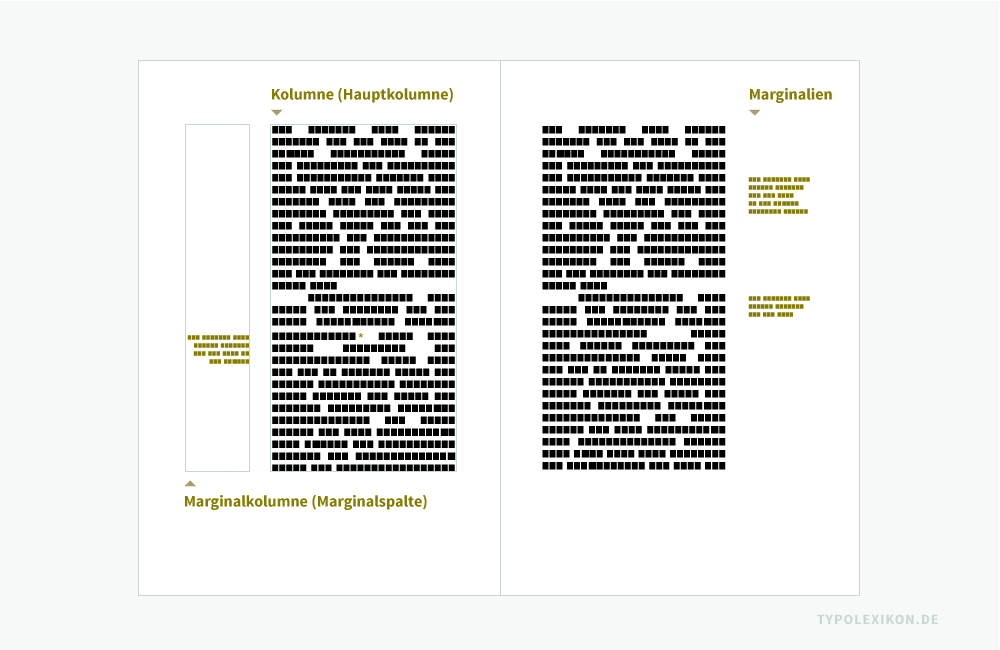
Marginalspalten
Marginalien werden bei Büchern oder buchähnlichen Publikationen in einer Marginalkolumne (Marginalspalte oder Marginalsatzspalte) außerhalb des Satzspiegels – in der Regel bei einer Verso-Seite im linken oder bei einer Recto-Seite im rechten Außensteg – eines Buchsatzspiegels 1) gesetzt. Bei großformatigen Büchern (z.B. Tischbüchern) können Marginalien auch im Bundsteg stehen. 2)
Registerhaltigkeit
Marginalien beginnen grundsätzlich immer auf der Schriftlinie der Zeile des Grundlinienrasters, auf welche sie Bezug nehmen. Die erste Marginalzeile ist folglich registerhaltig. Die zweite Zeile nebst Folgezeilen einer Marginalie kann dann vom Zeilenabstand (ZAB) der Hauptkolumne abweichen, beispielsweise in halben ZAB-Schritten (Halbzeilenraster). Unabhängig davon, sollten Marginalspalten auch bei einem ungewöhnlichen Zeilendurchschuss immer vertikal Register halten.
Konsultationszeichen
Falls keine Notenkolumne existiert oder kaum Fußnoten verwendet werden, können Marginalien zusätzlich mit Konsultationszeichen (Konsultation von lat. »consultatio« für »Beratschlagung«) verknüpft werden, beispielsweise mit Arabischen Ziffern.
Satzausrichtung
In der Buchtypografie sind Marginalien in ihrer Satzausrichtung zur Hauptkolumne hin angeordnet. Beim Blocksatz der Hauptkolumne ist die Satzausrichtung der Marginalien auf der linken Buchseite in der Regel rechtsbündig, auf der rechten Buchseite linksbündig. 3) Beim asymmetrischen Flattersatz der Hauptkolumne ist die Satzausrichtung der Marginalien auf der linken und rechten Buchseite in der Regel linksbündig.
Satzbreite
Marginalien werden in der deutschen Sprache in einer durchschnittlichen Satzbreite von mindestens zwei (z.B. bei langen Komposita) bzw. drei (bei durchschnittlichen Wortlängen) bis maximal sechs Worten (bei durchschnittlichen Wortlängen) gesetzt.
Schriftgrad
Marginalien werden in der Lesetypografie in einer Konsultationsgröße (Caption ≅ 6–8,4 DTP-Punkt) gesetzt. D.h., der Schriftgrad der Marginalie ist in der Regel deutlich kleiner als der der Grundschrift der Hauptkolumne. 4) 5) 6)
Schriftmischung
Marginalien müssen nicht in der Grundschrift der Hauptkolumne(n) gesetzt werden. Sie können durchaus mit Fonts aus anderen Hauptschriftgruppen bzw. alternativen Schriftstilen gestaltet werden.
Die Spaltenabstände, Spaltenbreiten etc. sowie die Wahl der Schrift bzw. Schriftstils einer Marginalie gehört in das Segment der Makrotypografie und sollte bereits bei der Konzeption einer semantischen und typografischen Schriftauszeichnungsmatrix (siehe Schriftmischung) berücksichtigt werden. Das »Feintuning« der Marginalie, also der exakte Schriftschnitt, der Optische Randausgleich etc., gehört in das Segment der Mikrotypografie.
↑1 | Anmerkung: Streng genommen ist der »Buchsatzspiegel« das gesamte schematische Ordnungssystem einer Doppelseite, also die unbedruckten und bedruckten Flächen. Der »Satzspiegel« hingegen nur die gedruckte Kolumne, also die bedruckte Fläche. |
↑2 | Tipp: Werden Marginalien verwendet, müssen die Außenstege – ggf. auch der Bundsteg – eines Buches grundsätzlich breiter angelegt werden. |
↑3 | Tipp: Bei rechtsbündigen Marginalien sollte unbedingt auf eine optisch gleichmäßige Satzkante geachtet werden (siehe Optischer Randausgleich). Im besten Falle sind die Interpunktionszeichen über die Satzkante zu stellen. |
↑4 | Anmerkung: Da Schriftgrade heute relativ sind, sind Empfehlungen aus dem Bleisatz – à la »eine Marginalie sollte ein oder zwei Grad kleiner sein« (Albert Kapr) – nicht mehr zielführend. |